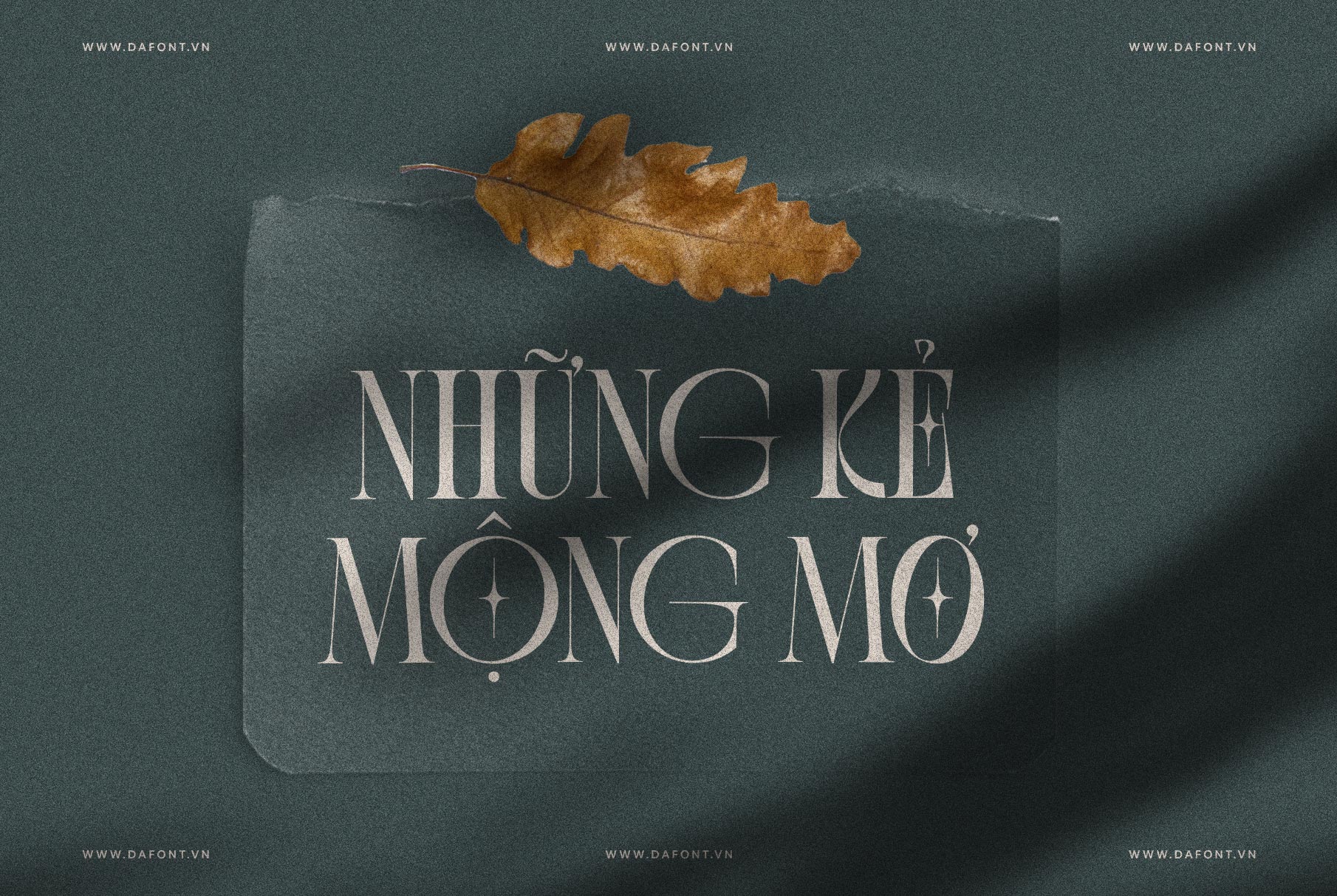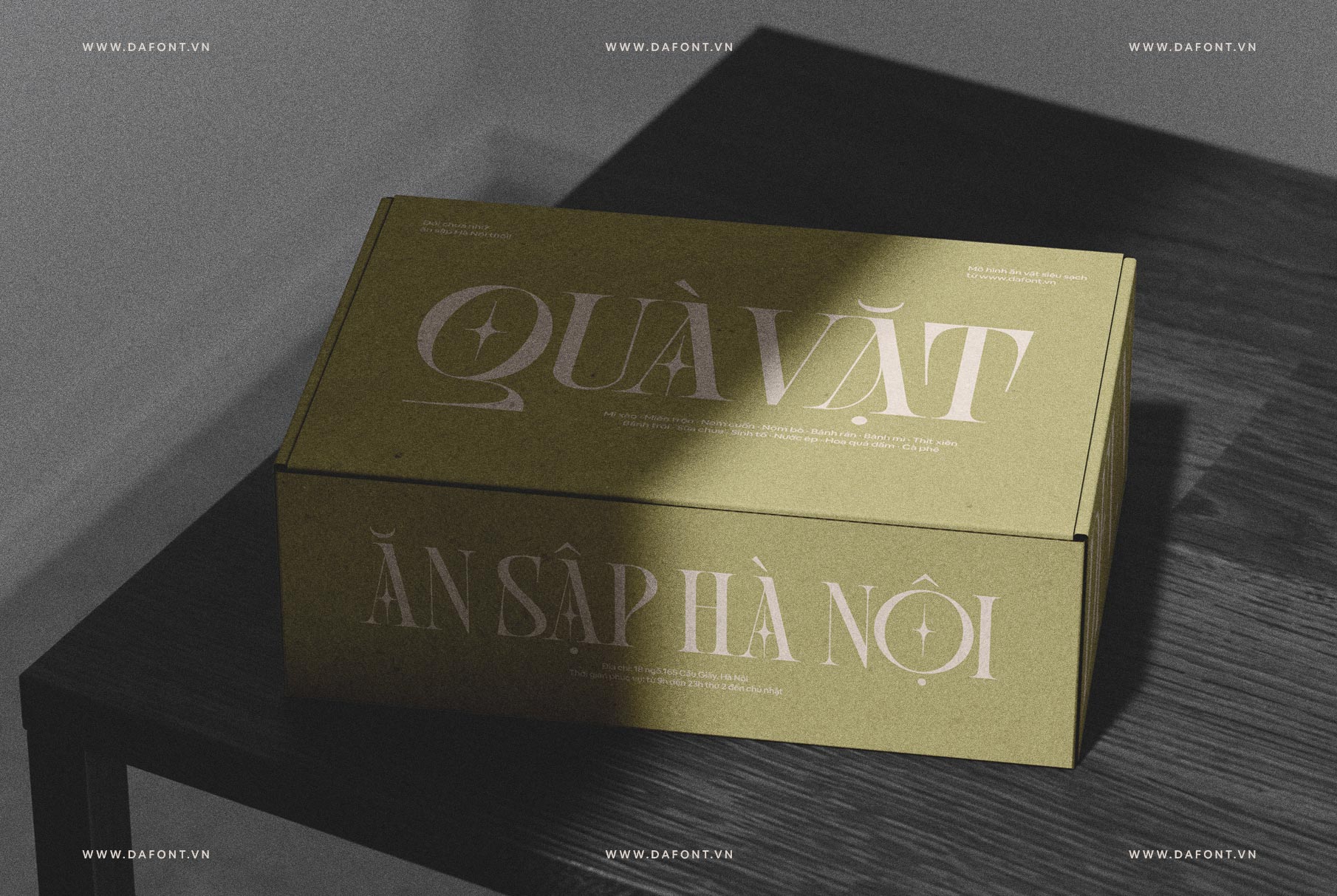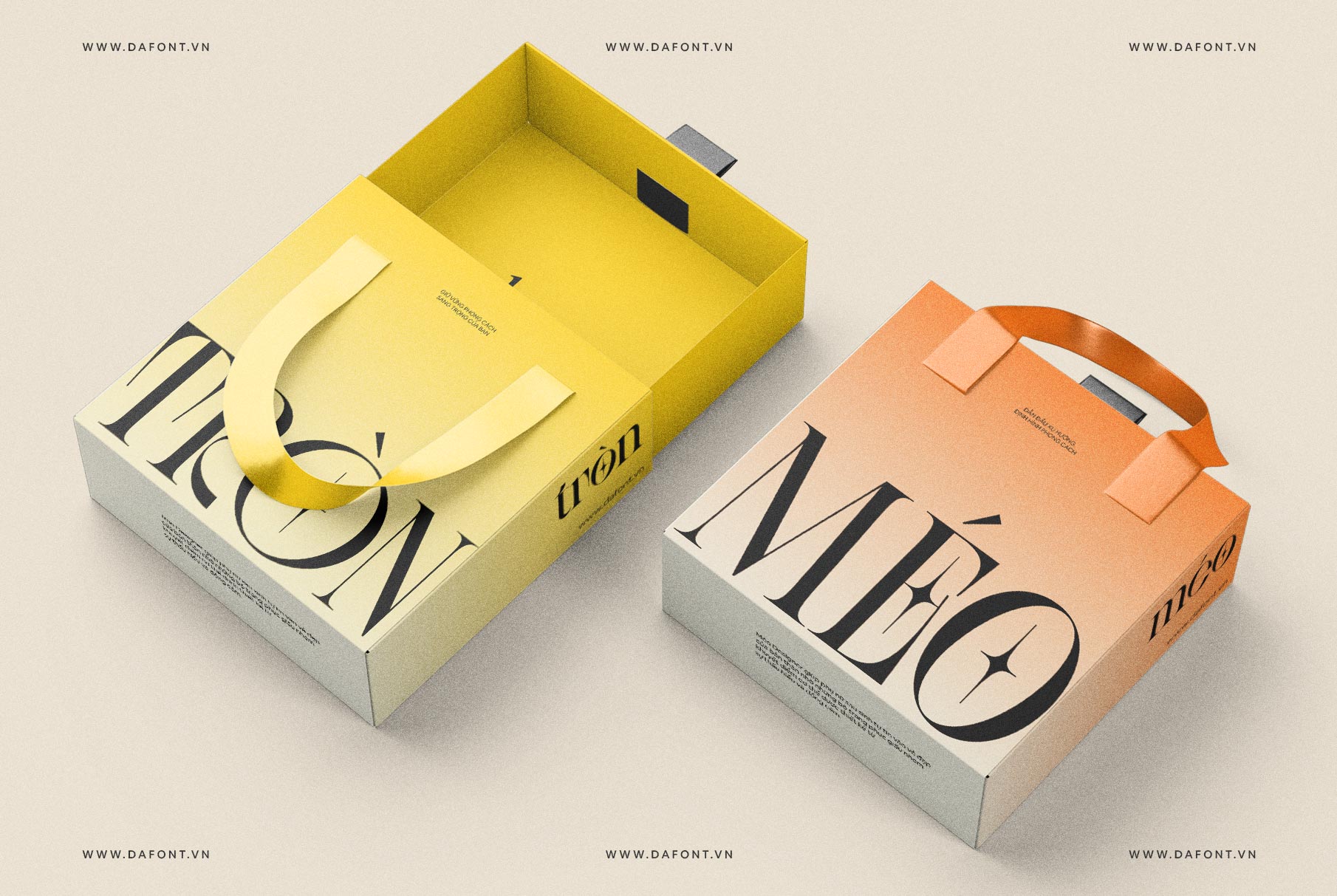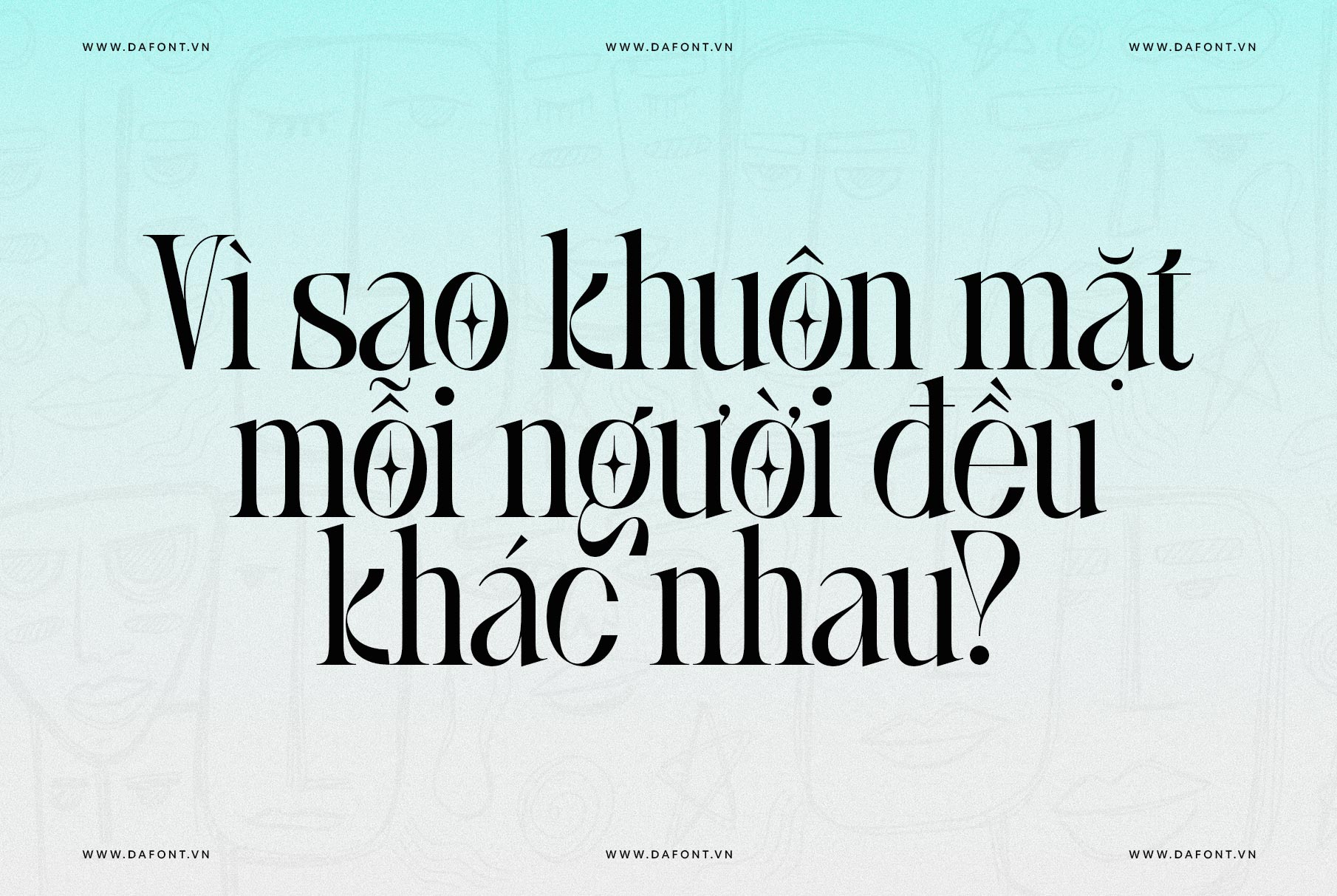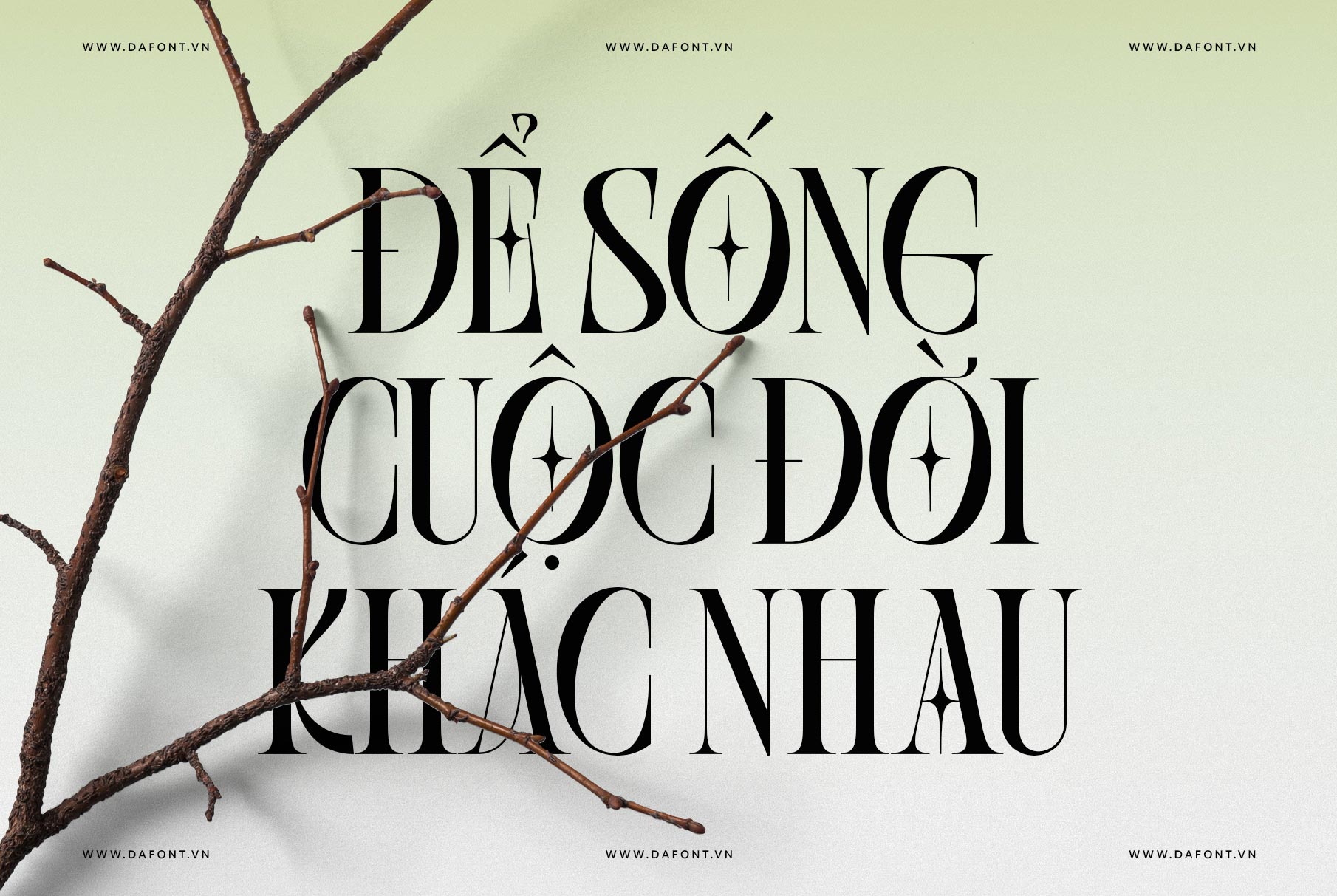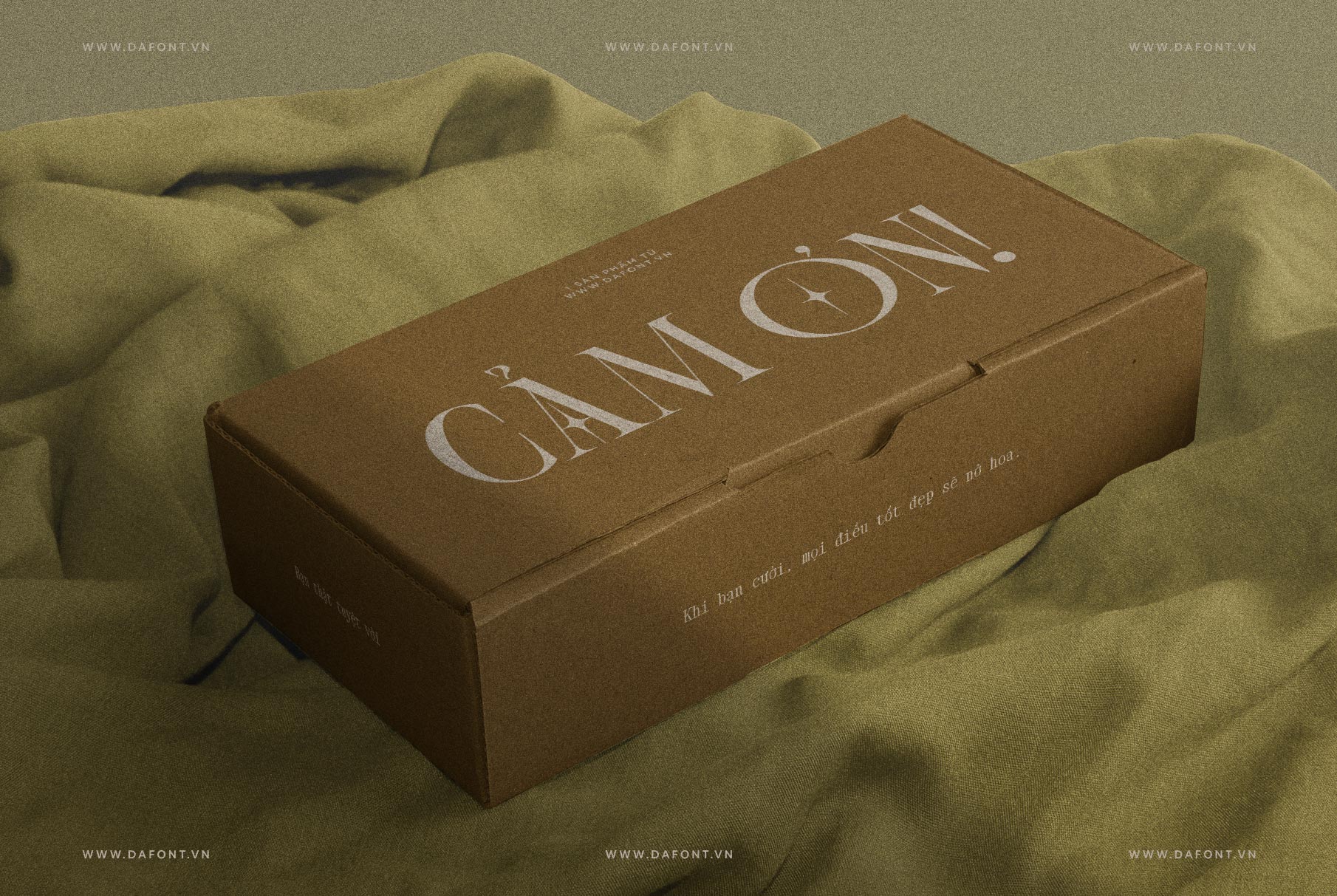
DFVN BOXROOM
Font chữ độc đáo với phong cách hiện đại
Trong thế giới thiết kế đồ họa ngày nay, font chữ đóng vai trò quan trọng trong việc tạo dựng nhận diện thương hiệu, mang lại tính thẩm mỹ cho sản phẩm và truyền tải thông điệp một cách hiệu quả. Một trong những font chữ đang nhận được sự chú ý gần đây là DFVN BOXROOM. Với vẻ ngoài hiện đại, mạnh mẽ và đầy sáng tạo, SLTF BOXROOM đang trở thành lựa chọn lý tưởng cho các nhà thiết kế và marketer.
Đặc điểm nổi bật DFVN BOXROOM
SLTF BOXROOM là một phông chữ serif được thiết kế để khác biệt. Nó kết hợp tinh tế giữa sự thanh lịch cổ điển và phong cách hiện đại, tạo nên điểm nhấn đậm chất trong mỗi thiết kế.
Những đường serif sắc sảo cùng những chi tiết trang trí tinh tế trên các chữ O, Q, E và F tạo nên sự ngạc nhiên và thích thú cho người xem. Đây không chỉ là một font chữ, mà là công cụ biểu đạt cảm xúc và phá cách.
• Độc đáo và phong cách: BOXROOM mang đến sự kết hợp giữa độc đáo và tinh tế. Nó được thiết kế để gây ấn tượng, với những đường serif kéo dài đầy tính nghệ thuật.
• Linh hoạt: Bao gồm hơn 65 chữ ghép (ligature) và chữ thay thế (alternate), giúp bạn tự do sáng tạo theo nhiều phong cách khác nhau.
• Tỷ mỹ trong thiết kế: Từng chi tiết của BOXROOM được thiết kế cẩn thận để đảm bảo tính dễ đọc, sự hấp dẫn thị giác và một trải nghiệm kiểu chữ độc đáo.
Ứng dụng nổi bật của DFVN BOXROOM
Font DFVN BOXROOM nổi bật không chỉ bởi vẻ ngoài hiện đại và độc đáo, mà còn nhờ tính linh hoạt vượt trội trong các ứng dụng thiết kế. Dưới đây là những lĩnh vực mà BOXROOM thể hiện tối đa tiềm năng của mình:
• Thương hiệu và Logo: Tạo ra những bản sắc thương hiệu ấn tượng và đáng nhớ, nổi bật giữa đám đông.
• Thiết kế biên tập: Nâng tầm các bố cục tạp chí, tiêu đề và tiêu điểm bài viết bằng sự tinh tế.
• Bao bì và Quảng cáo: Thu hút sự chú ý với các thiết kế nổi bật, khiến người xem phải ngoái nhìn.
• Thiết kế Website: Tăng thêm nét cá tính và thanh lịch cho trang web của bạn, làm say mê khách truy cập.
DFVN BOXROOM không chỉ là một font chữ – đó là ngôn ngữ của sự sáng tạo, là cánh cửa mở ra vô vàn khả năng mới mẻ. Đây không chỉ là công cụ, mà là lời mời gọi bạn phá vỡ mọi ranh giới, định hình lại những chuẩn mực cũ kỹ và tạo nên những điều thực sự độc nhất.
Hãy để BOXROOM trở thành nguồn cảm hứng, biến ý tưởng của bạn thành những tác phẩm nghệ thuật mang đậm dấu ấn cá nhân.
DFVN BOXROOM được Việt hóa đầy đủ, tinh chỉnh lại các dấu cho phù hợp hơn với font. Ngoài ra các ký tự thay thế độc đáo cũng được Việt hóa và dễ dàng sử dụng bằng tính năng Opentype. Ngoài ra, các dấu Ư, Ơ hoa và thường cũng được thiết kế 2 kiểu dấu để linh hoạt hơn trong việc sử dụng.